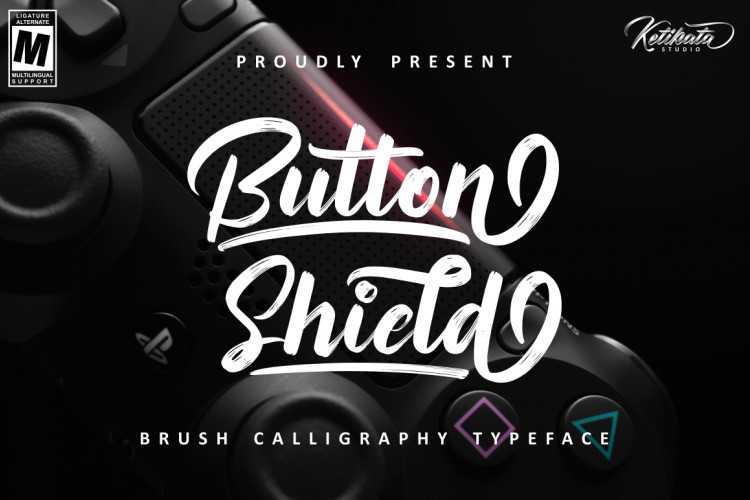
Button Shield Brush Font – Download Grátis
Esta é uma tipografia chamada ‘Button Shield Font’, criada pela Ketikata Studio. Ela combina a elegância do grafismo com a simplicidade e a autenticidade da escrita à mão. Combine-a com outros tipos de fontes para dar um toque único em seus projetos gráficos. Ideal para criar marcas distintivas, essa tipografia única se destaca não só por seu estilo único, mas também pela sua fluidez contínua e personalidade intrínseca. É perfeitamente adequada para impressões, logotipos, citações, selos de identificação, embalagens, headlines em blogs ou simplesmente adicionar um texto elegante à uma foto. Button Shield é a fonte ideal para quem busca uma mistura sofisticada e autêntica. Seu design único lhe dá liberdade para explorar diferentes estilos e ambientes gráficos. Não importa o projeto que você esteja trabalhando, essa fonte se encaixa perfeitamente. A ‘Button Shield Font’ é um presente para designers de todos os tipos, uma maneira criativa de destacar seus trabalhos e dar uma cara única aos seus projetos. Experimente combinar esta fonte com outros designers ou personalizá-la para atender às suas necessidades específicas, garantindo que cada projeto seja único e impressionante.